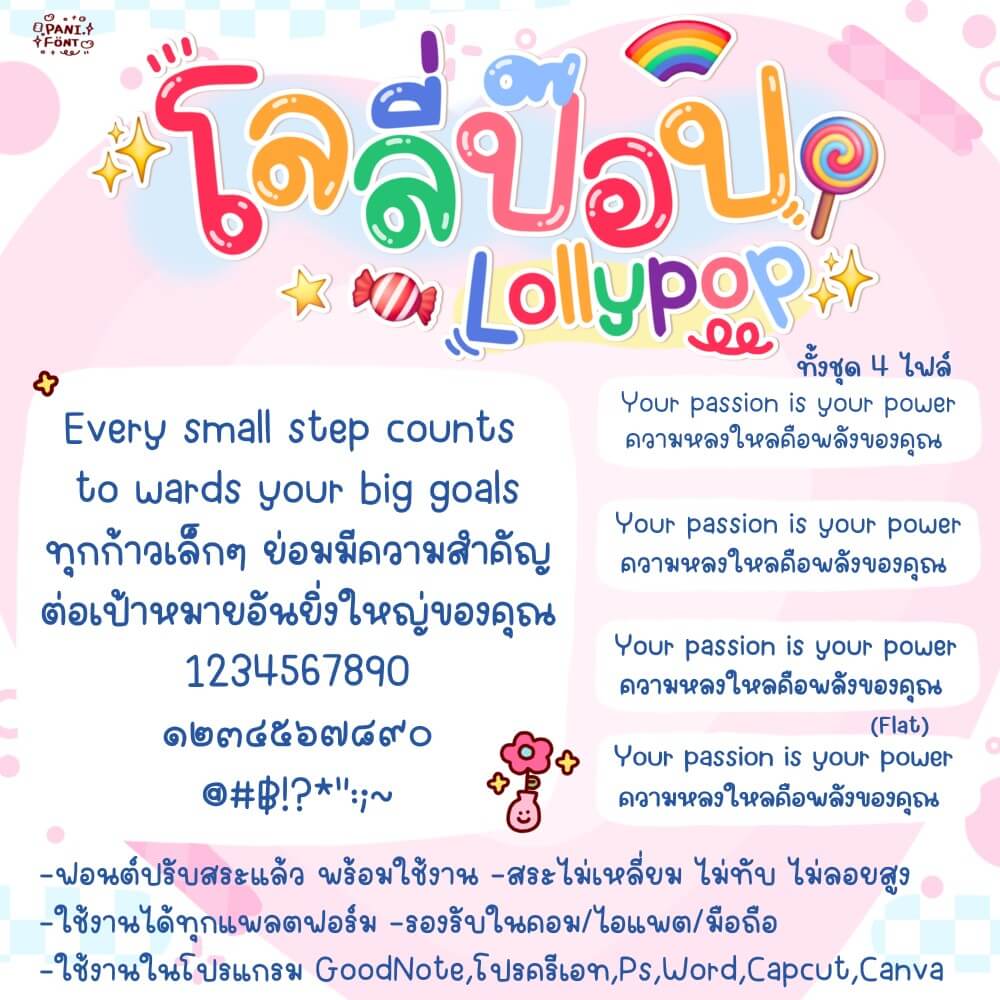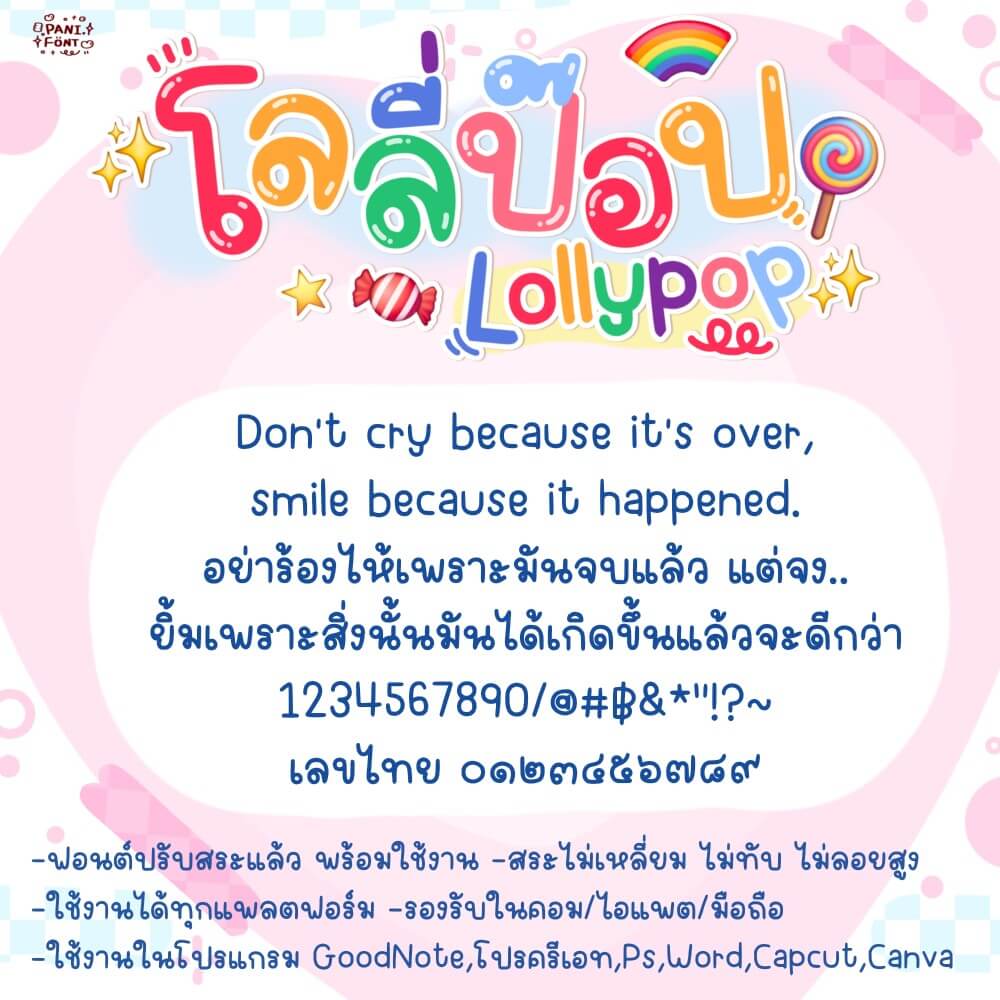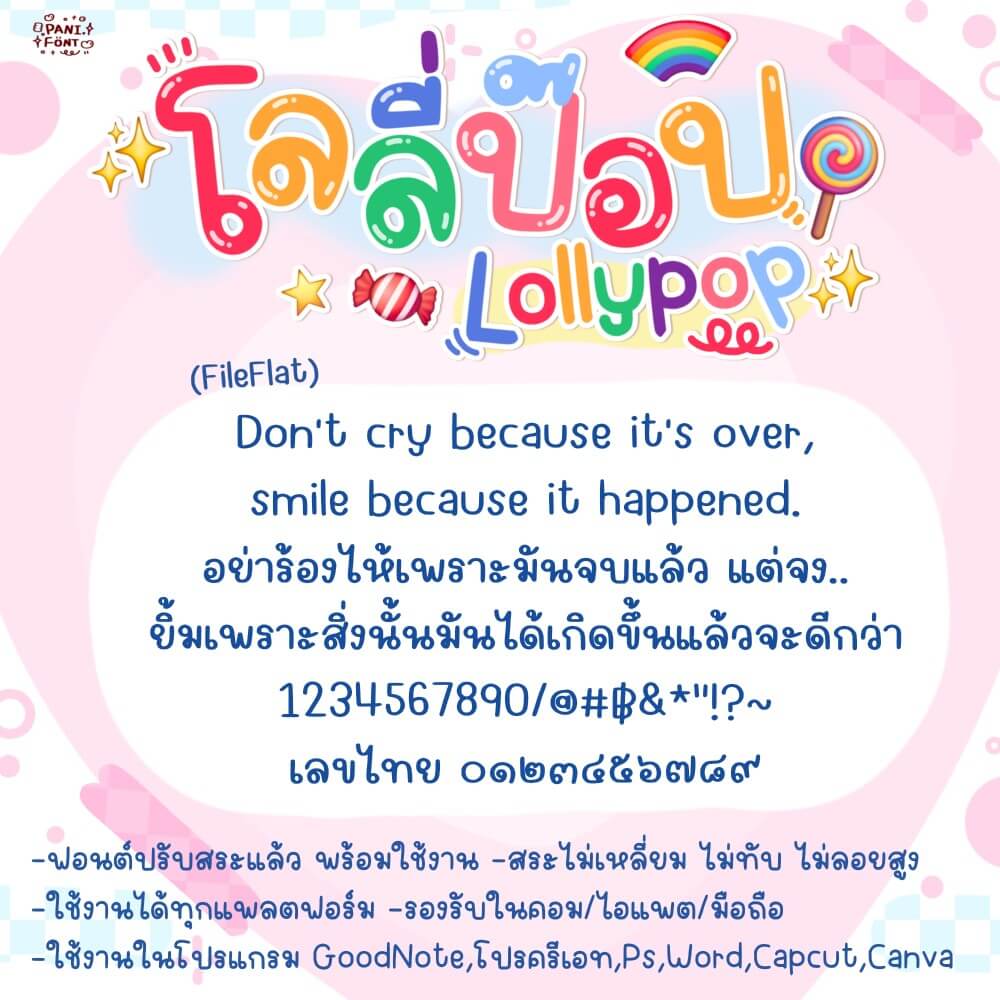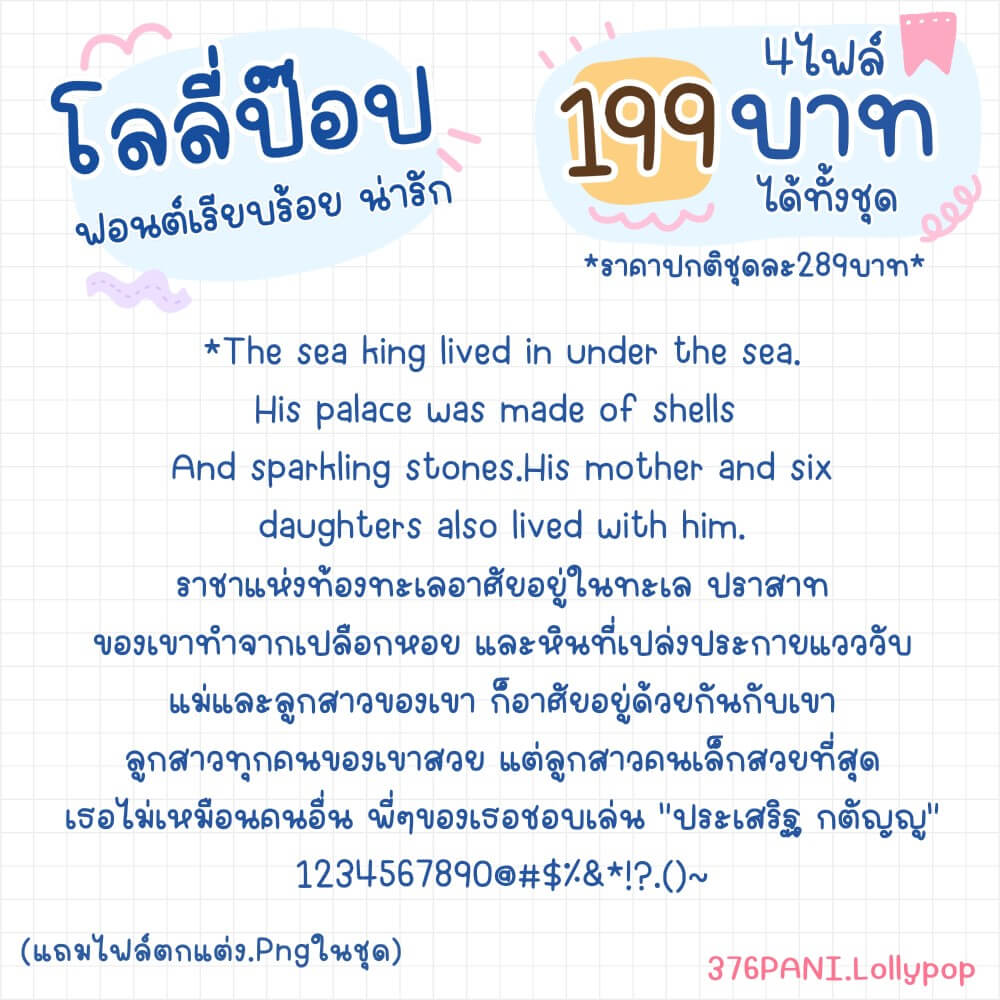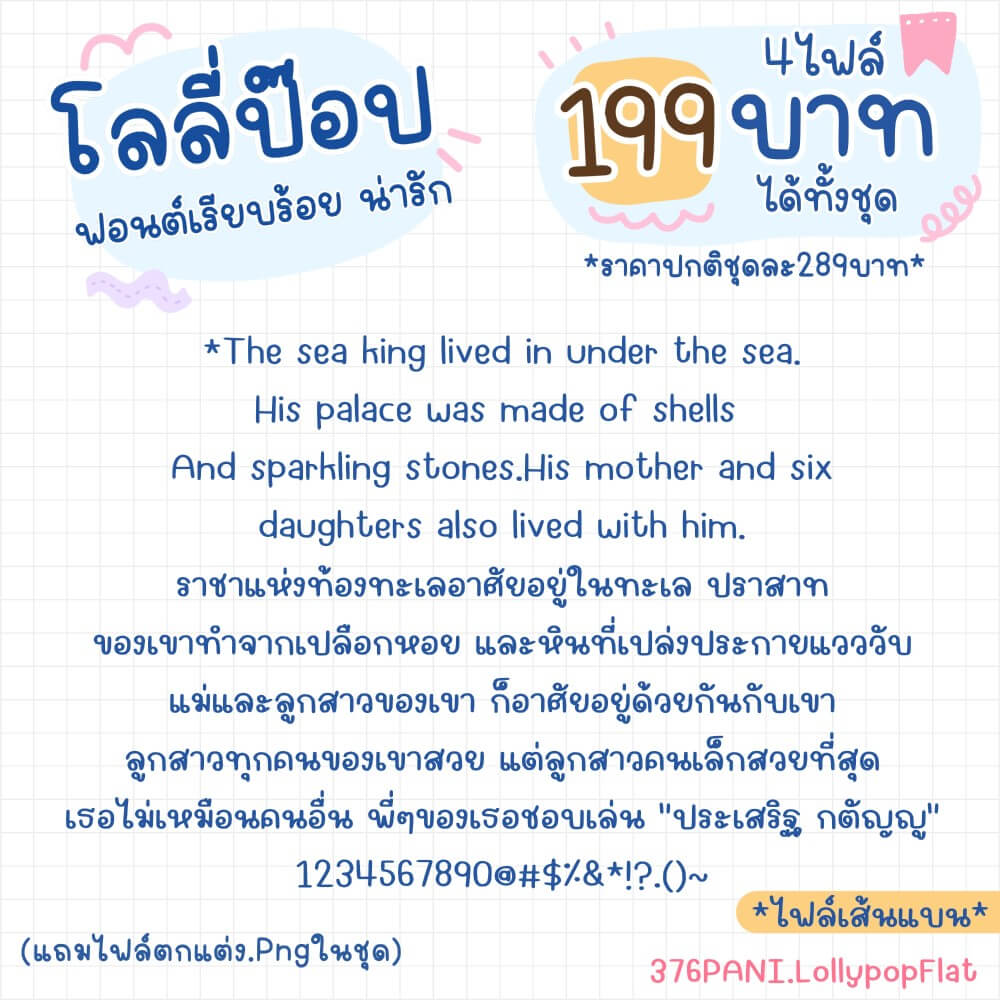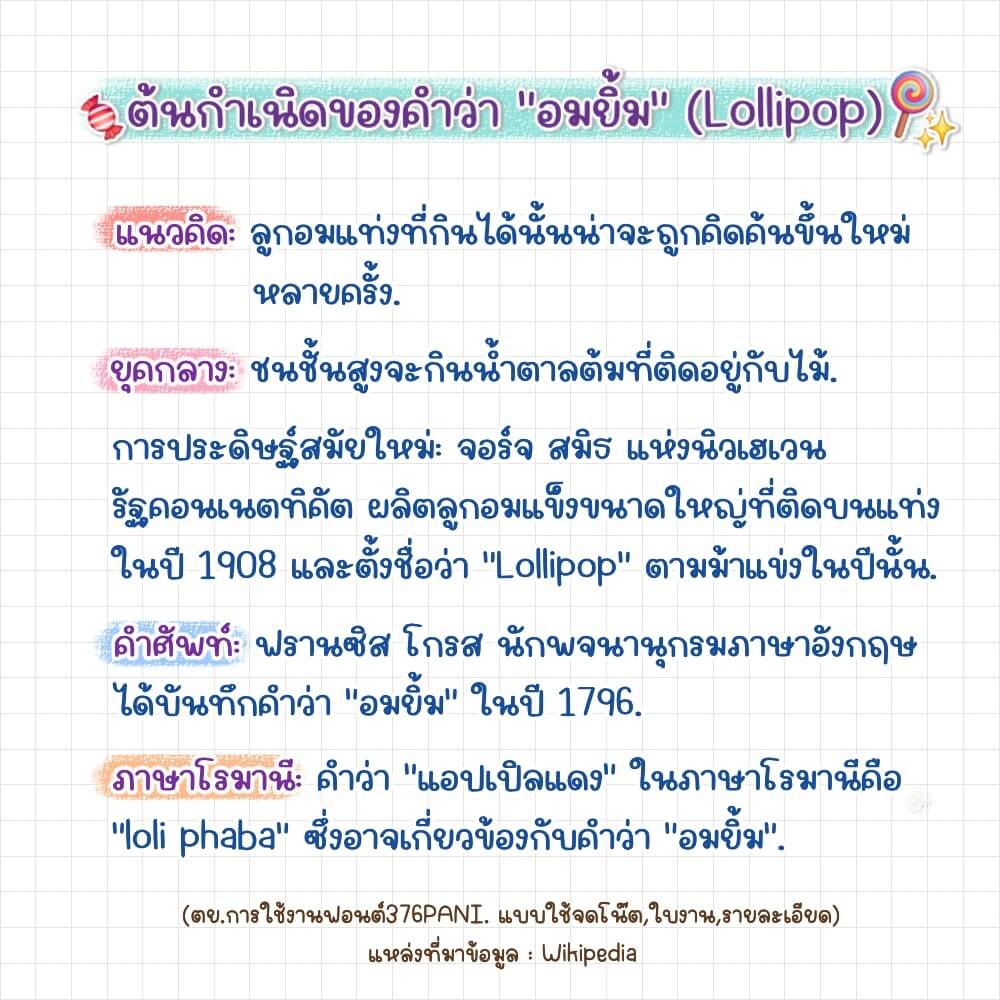
376PANI.โลลี่ป๊อป
ฟอนต์ 376PANI.โลลี่ป๊อป – ฟอนต์แนวเรียบร้อย แต่ยังน่ารัก น่าเอ็นดู ใช้จดโน้ต รายละเอียด อ่านง่าย ช่องไฟกำลังดี หรือจะแต่งคลิป แต่งรูป ก็ดูสดใส สะอาดตา